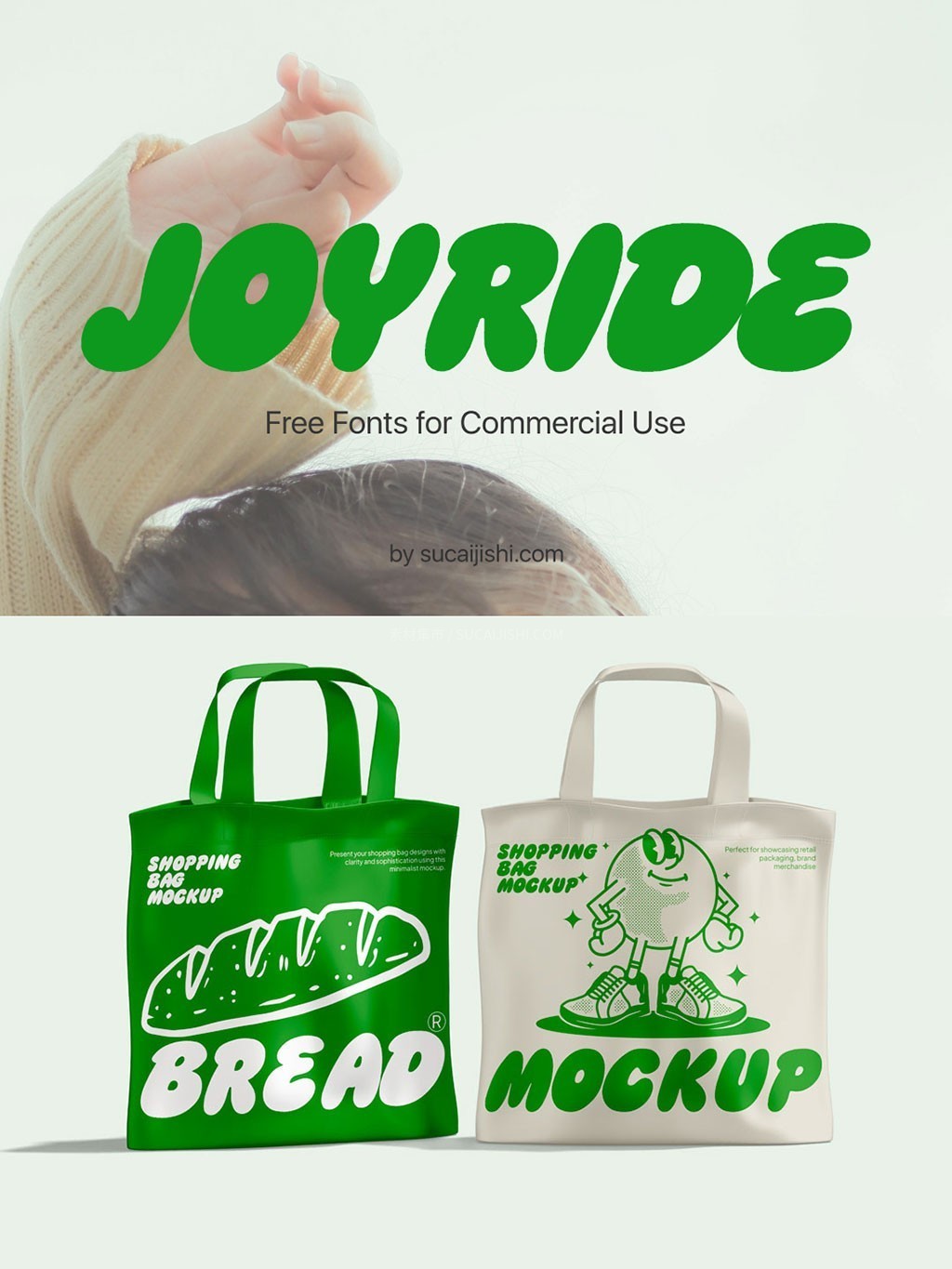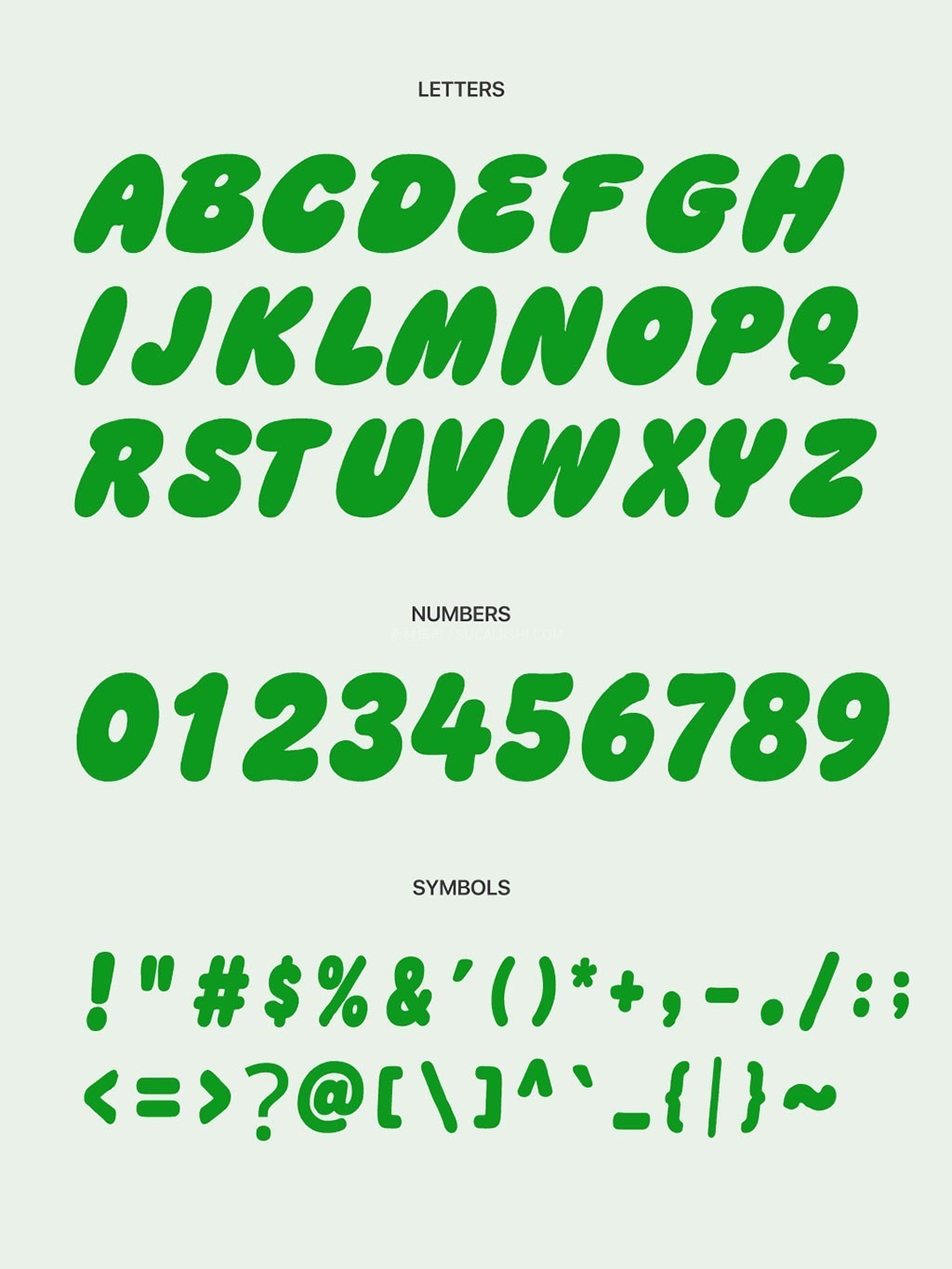
Sucaijishi JoyRide 免费商用粗圆英文字体
一款由素材集市原创充满活力与趣味的英文字体。结合了极具分量感的粗体字重、平滑温和的圆角设计以及自带动感的倾斜角度,为你打造出极具亲和力和视觉冲击力的排版效果。适合用于需要传递轻松、快乐情绪的品牌视觉。
适用场景: 品牌LOGO设计、包装设计(如零食、饮料)、海报标题、儿童/宠物品牌视觉、UI界面大标题、社交媒体创意排版等。